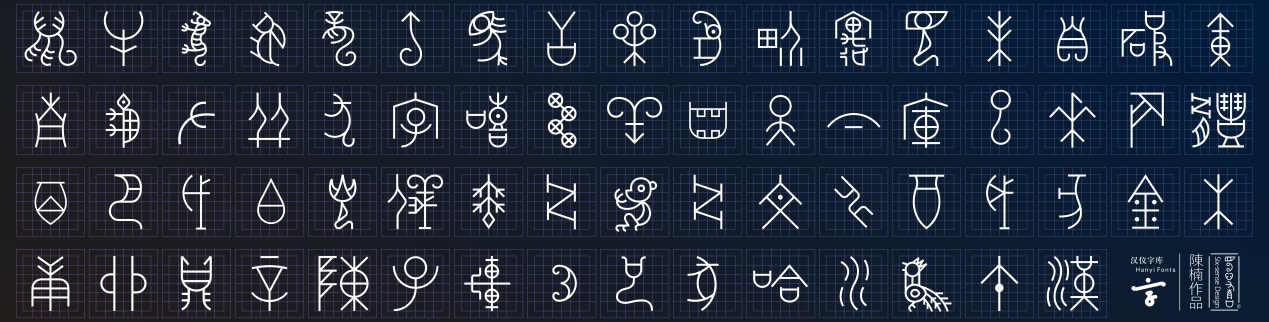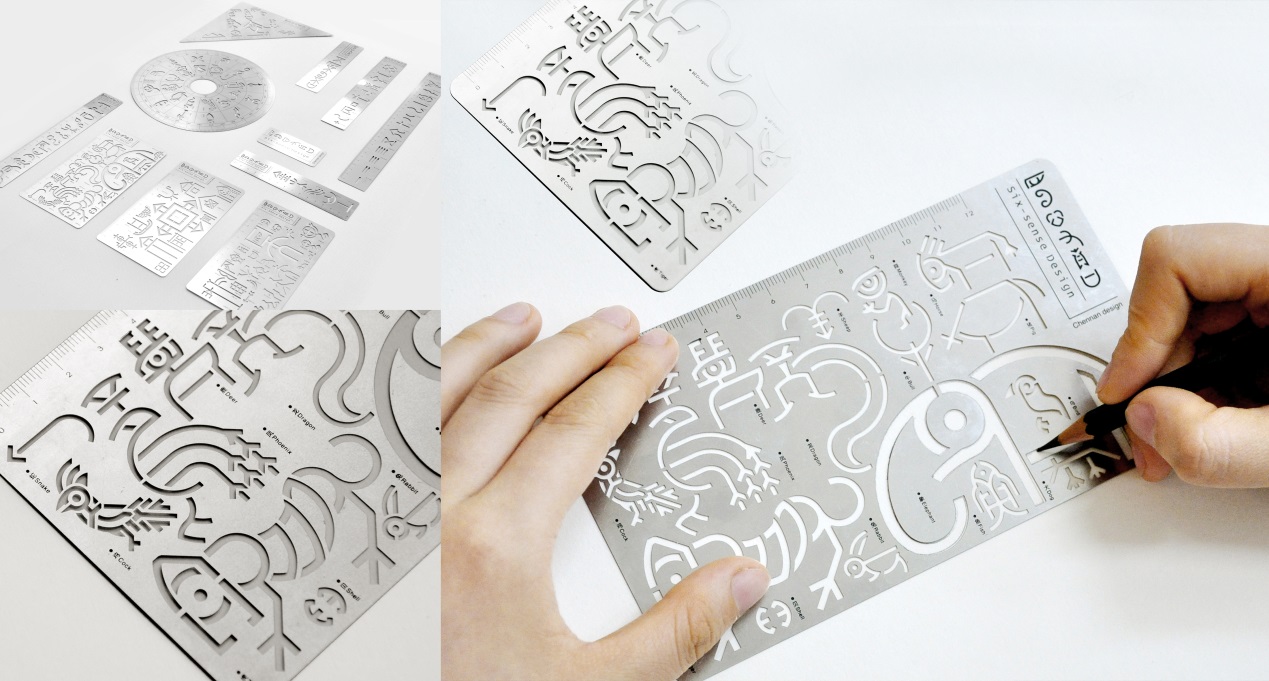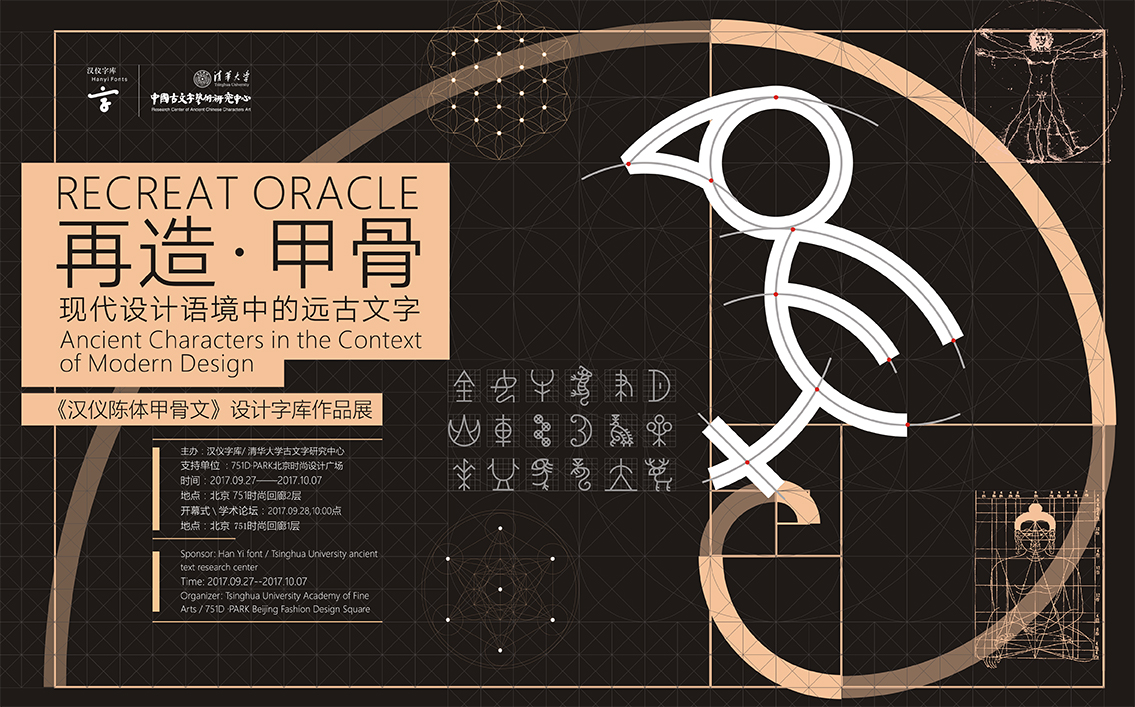
甲骨文字体能做什么,汉仪字库告诉你
满屏天书般的字体,看似眼熟,趴上去能认出二三,用尽全力却未必能通顺的读一遍•••没错,全球第一套甲骨文设计字库来了!
“汉仪陈体甲骨文”是国内外第一套甲骨文设计字库。由汉仪字库与清华大学陈楠老师合作开发完成。这款字库揭示了甲骨文所蕴含的数学之美与网格秘密,开启了一条全新的字库设计路径,第一次推出了不以书写作为主要功能的字库设计先例,将设计开发的重点放在图案表意以及文化衍生之上,在商业开发的同时担负起文化承传的社会责任。
2017年9月28日北京设计周期间将隆重举行名为“再造•甲骨”的设计展览与学术论坛。主题展览与学术论坛并行。以陈楠老师对中国汉字设计史研究的独特视角为主线,娓娓道来本套字库设计故事。同时,汉仪字库也以字库技术对“字文化”生命线的延续和再创为主题,展示字库研发成果及其衍生拓展产品,用创意营造真实的文化体验,带领观众追根溯源、重温远古文明在当下的绽放。“汉仪陈体甲骨文”字库正式版也将在届时对外发布。